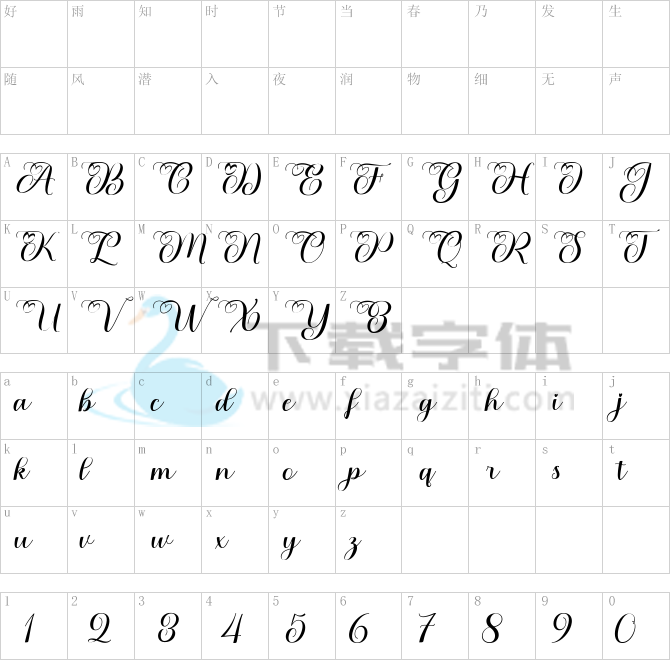
Agnesia.ttf字体下载
Agnesia.ttf字体下载,这款字体结构工整、笔画清晰,兼顾美观与易读性,适用于标题、正文、海报、包装、LOGO 等多种场景。字形优雅稳定,风格百搭耐看,适配日常排版与创意设计,让文字呈现更舒适、更具质感。Agnesia.ttf字体下载一笔一画,皆是细节,以均衡的比例、流畅的线条打造舒适视觉体验,字形端正大气,风格简约现代。无论是商业设计、品牌宣传还是日常排版,都能轻松驾驭,让文字更有格调与力量。Agnesia.ttf字体下载字体下载。